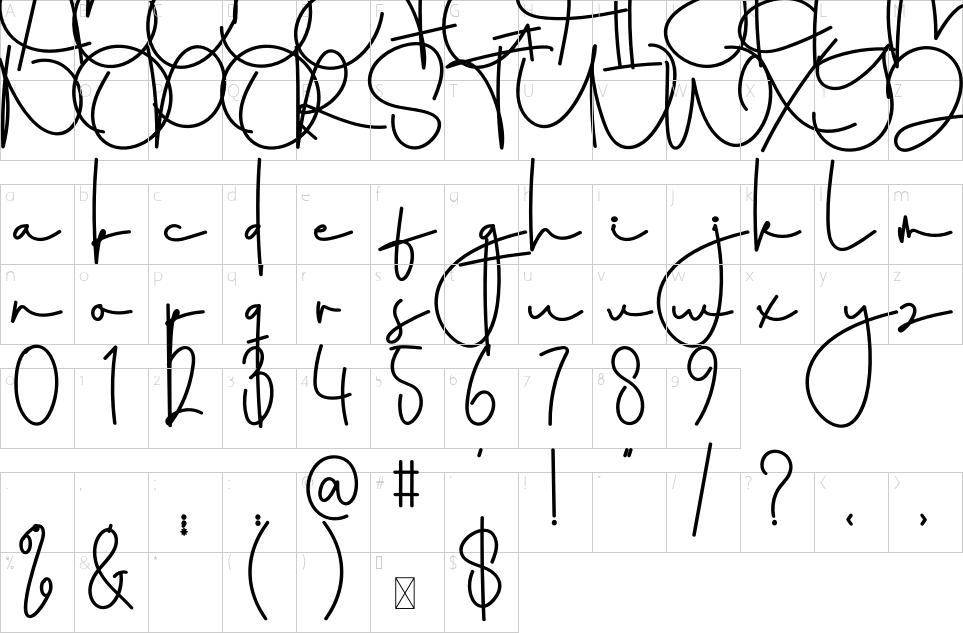
A fonte Greatings é uma elegante escolha para qualquer designer que busca uma fonte moderna e versátil sem comprometer a qualidade. Desenvolvida pelo designer scratchones, esta fonte garante um texto claro e sofisticado tanto no Windows quanto no Mac. Se você está procurando por uma alternativa aos mais tradicionais, Greatings é perfeitamente adequada para criar designs digitais de alta qualidade. Com seu design intuitivo, a fonte Greatings está disponível para download gratuito, permitindo que designers como você personalizem suas criações sem comprometer os custos. Sua versão gratuita ainda oferece uma variedade suficiente de estilos e opções para adaptar ao seu projeto específico.